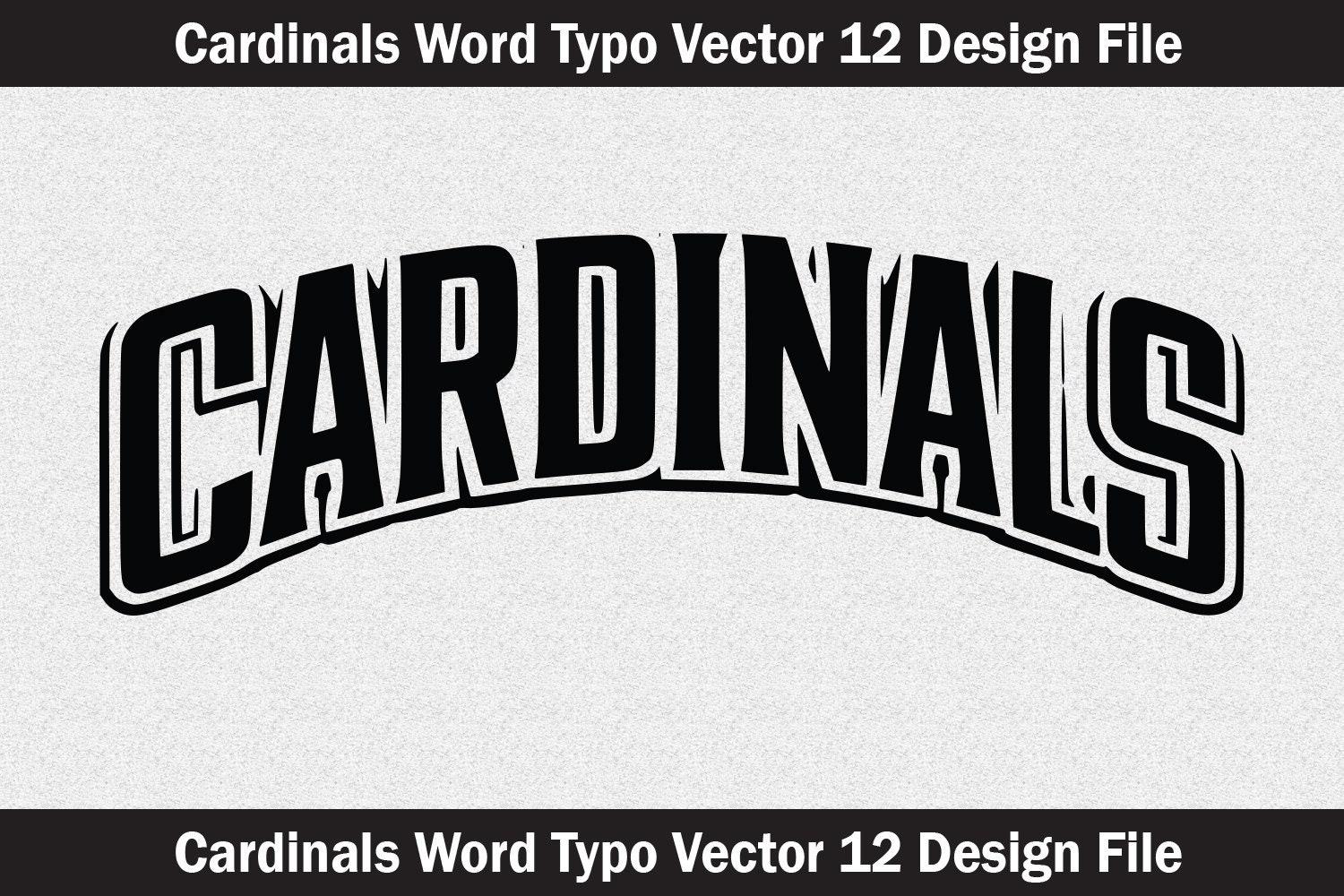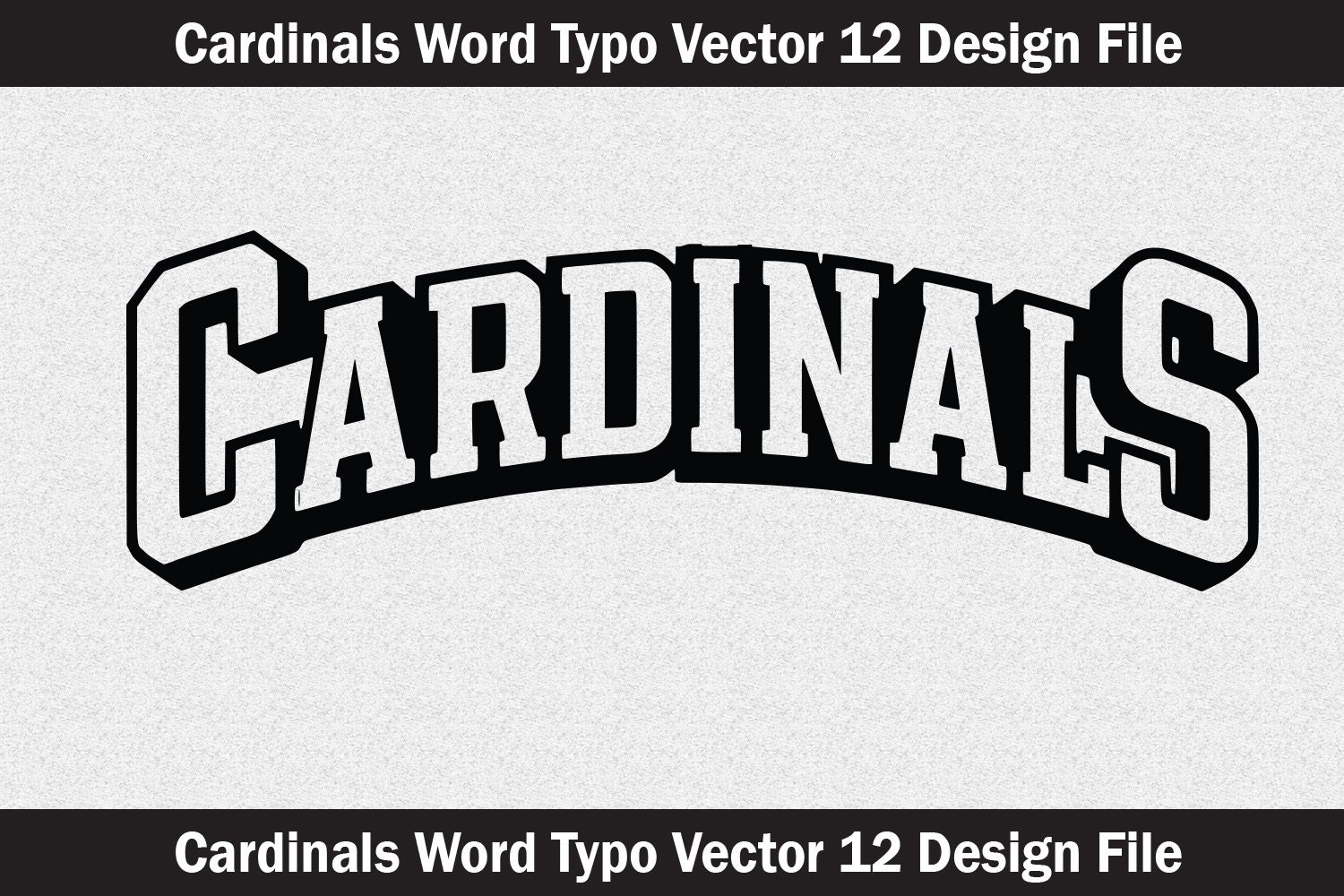
Crea proyectos audaces y llamativos con este paquete Cardinals SVG: tu colección imprescindible de word art inspirado en mascotas y diseños tipográficos limpios. Perfecto para artesanos, pequeños negocios y entusiastas del DIY, este set versátil ofrece archivos vectoriales de alta calidad listos para corte, impresión y sublimación. Ya sea que hagas calcomanías de vinilo, camisetas, tazas, pósteres o letreros de madera, tendrás los formatos que necesitas para resultados profesionales.
Da vida a tus ideas con temática de Cardinals con tipografía limpia, líneas vectoriales precisas y archivos que simplemente funcionan, siempre.